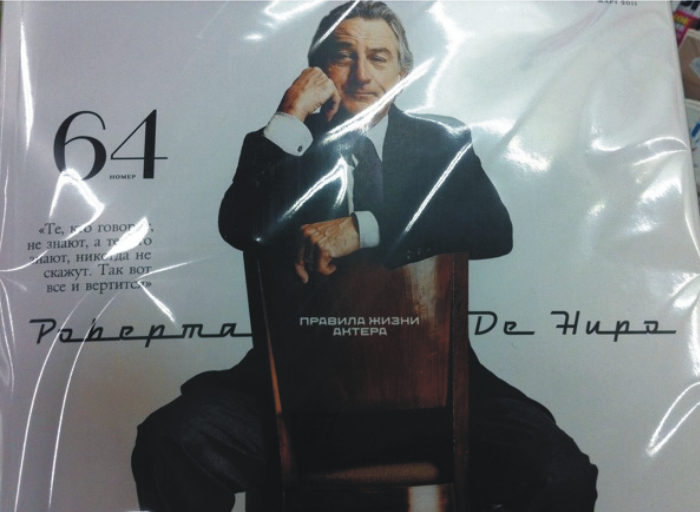
okulenak, Очень похоже на Rockwell Bold.
Срочно нужен шрифт ватермарка.
По-моему это Condens или Compact
Подскажите пжл. что за шрифт такой? - которым написано Роберто де Ниро.
Stellan, Это Raceway.
По наводке myfonts.com, Raceway или Neonstream
okulenak, Это айтисишный Neo Tech. То ли болд, то ли блэк, не помню.
Заказчик утверждает что это его логотип (смеяться конечно грешно над больными)
Мне нужно его вставить в буклет и как всегда в векторе, у меня даже руки не поднимаются такое перерисовывать. Помогите найти этот ужасный шрифт.
kopeika, Это Mistral, такую мерзость нужно обязательно знать.
Подскажите, что за шрифт?
anDyrv, Миньон медиум.